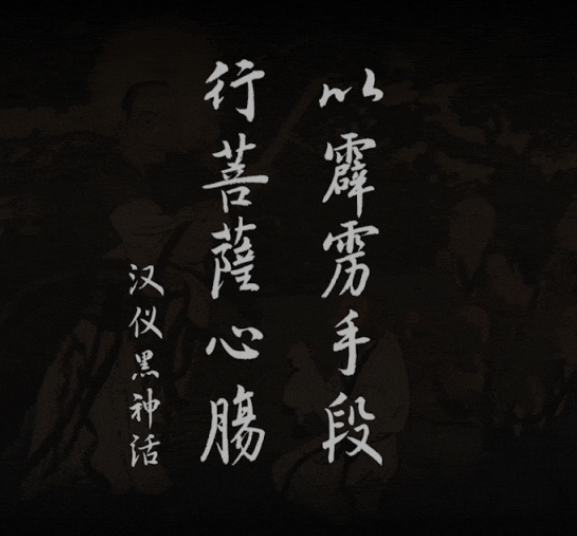
汉仪字库 ×《黑神话:悟空》定制字库争先版已上线!
汉仪字库 ×《黑神话:悟空》定制字库争先版已上线!,这款字体结构工整、笔画清晰,兼顾美观与易读性,适用于标题、正文、海报、包装、LOGO 等多种场景。字形优雅稳定,风格百搭耐看,适配日常排版与创意设计,让文字呈现更舒适、更具质感。汉仪字库 ×《黑神话:悟空》定制字库争先版已上线!一笔一画,皆是细节,以均衡的比例、流畅的线条打造舒适视觉体验,字形端正大气,风格简约现代。无论是商业设计、品牌宣传还是日常排版,都能轻松驾驭,让文字更有格调与力量。汉仪字库 ×《黑神话:悟空》定制字库争先版已上线!字体下载。
传承古代匠心
汉仪字库联合游戏科学研发团队
以字见心,刚柔并济